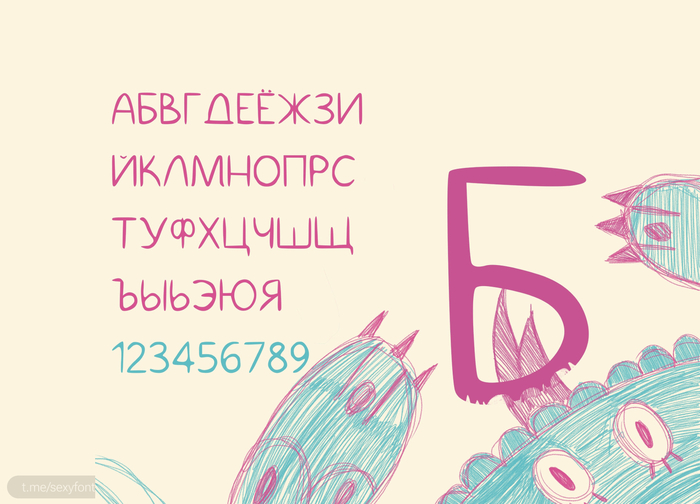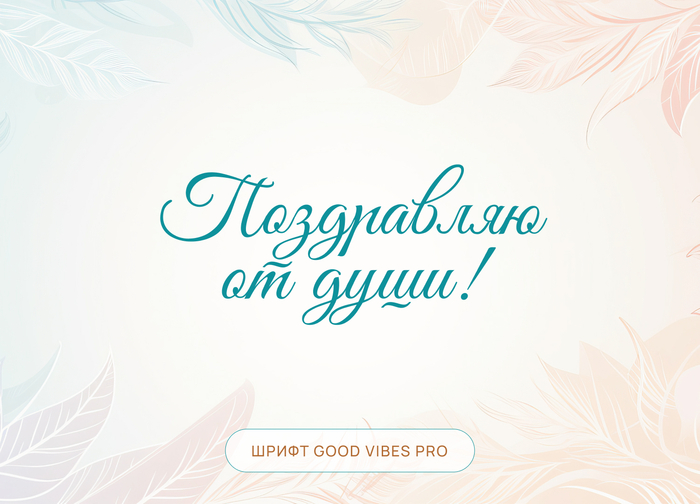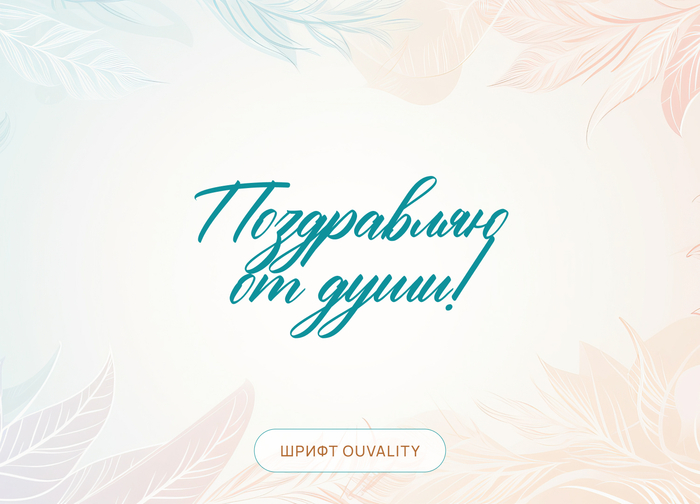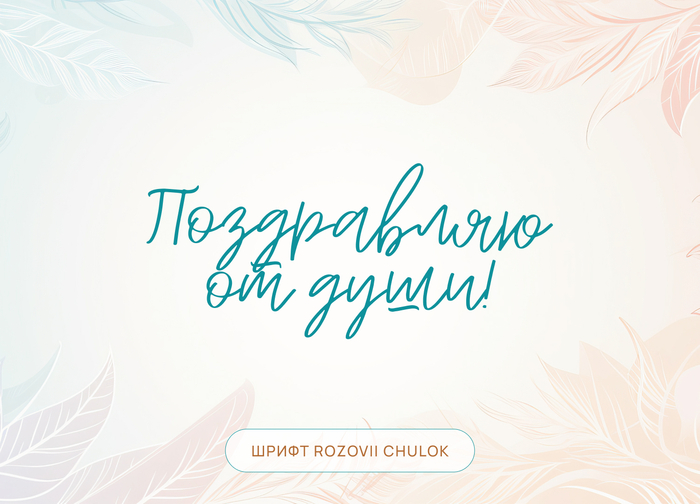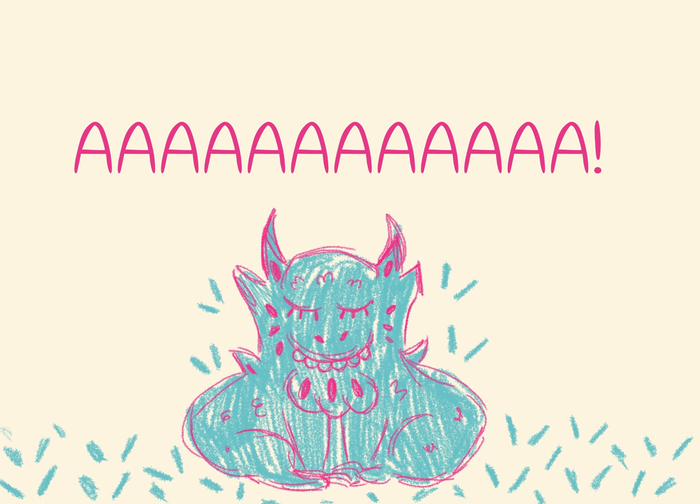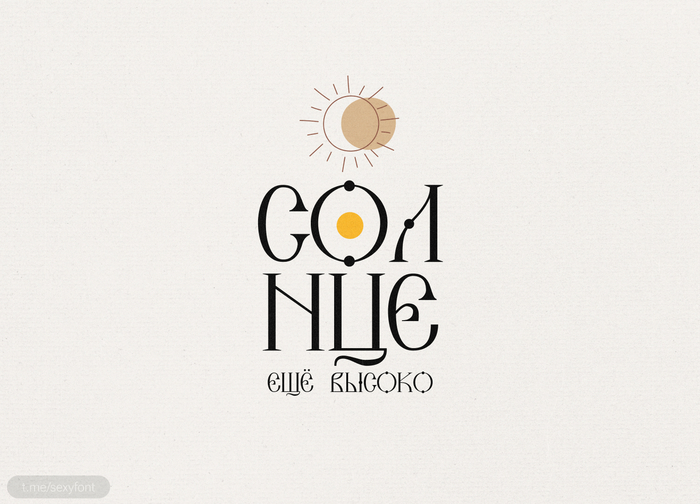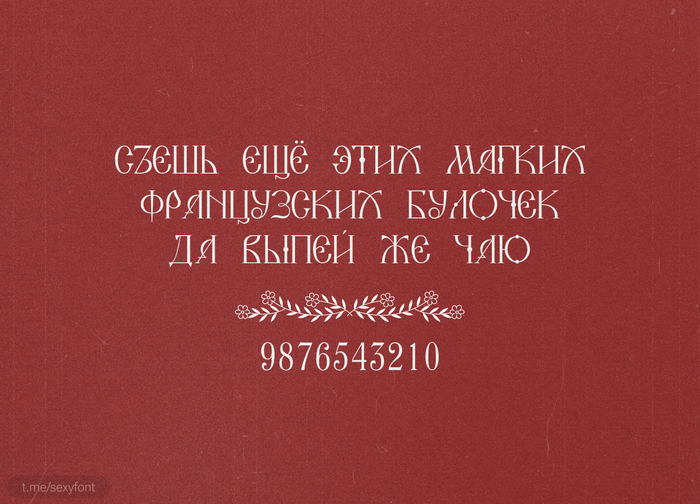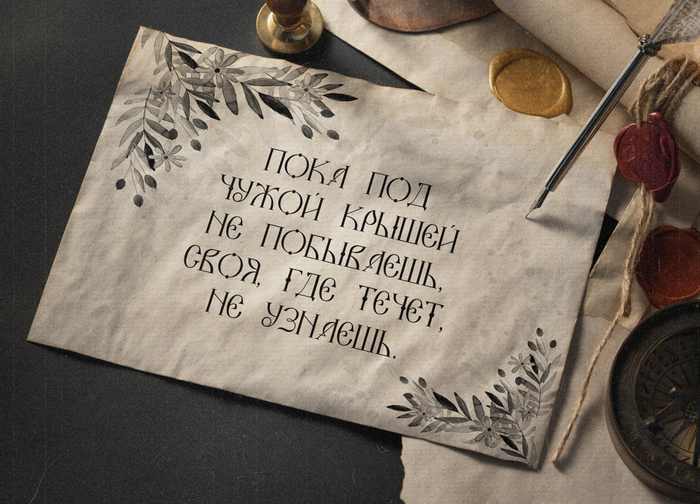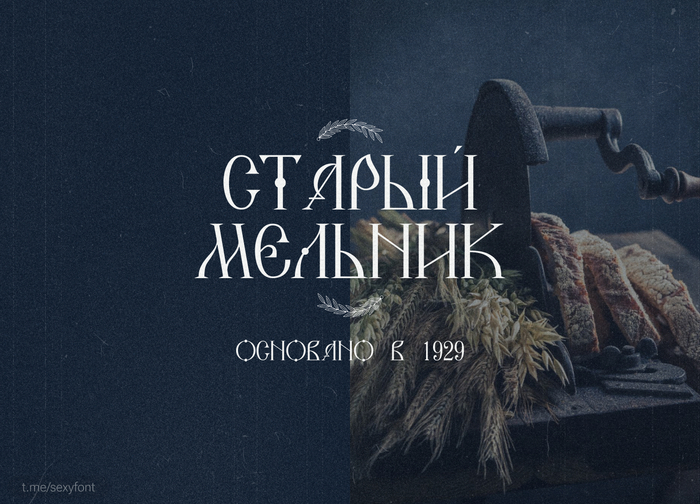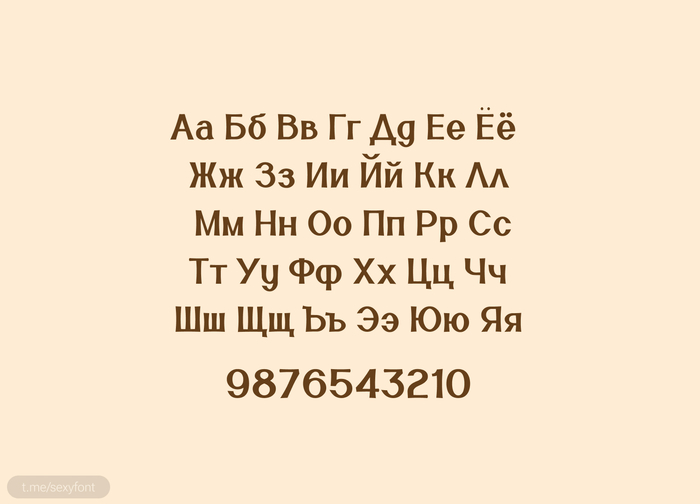
Шрифт AnchorYard
Поднять паруса!!!! Шрифт FTAnchorYard. Такой немного морской шрифтец. Необычный для небольших заголовков.
Автор: fresher tan
Поднять паруса!!!! Шрифт FTAnchorYard. Такой немного морской шрифтец. Необычный для небольших заголовков.
Автор: fresher tan
Строгий, технологичный и в меру читаемый шрифт.
С праздником всех милых дам. И Ловите вторую часть подборки с рукописными шрифтами.
Шрифт lighthaus. Красивая антиква для твоих проектов. Я все сказал. Автор: Jerak Durzan. Бесплатно для личного и коммерции
Полностью бесплатный кириллический шрифт. Может не супер выразительный, но зато неплохо читаемый) В меру декоративный. Есть целых 6 начертаний
Автор: Дмитрий Антонов
Yauza Tygra. Полностью бесплатный шрифт в легком старо-славянском стиле.
Бу! Шрифт Бабайка. Милый рисованный шрифт. Напугать не напугает конечно. Но настроение поднимет.